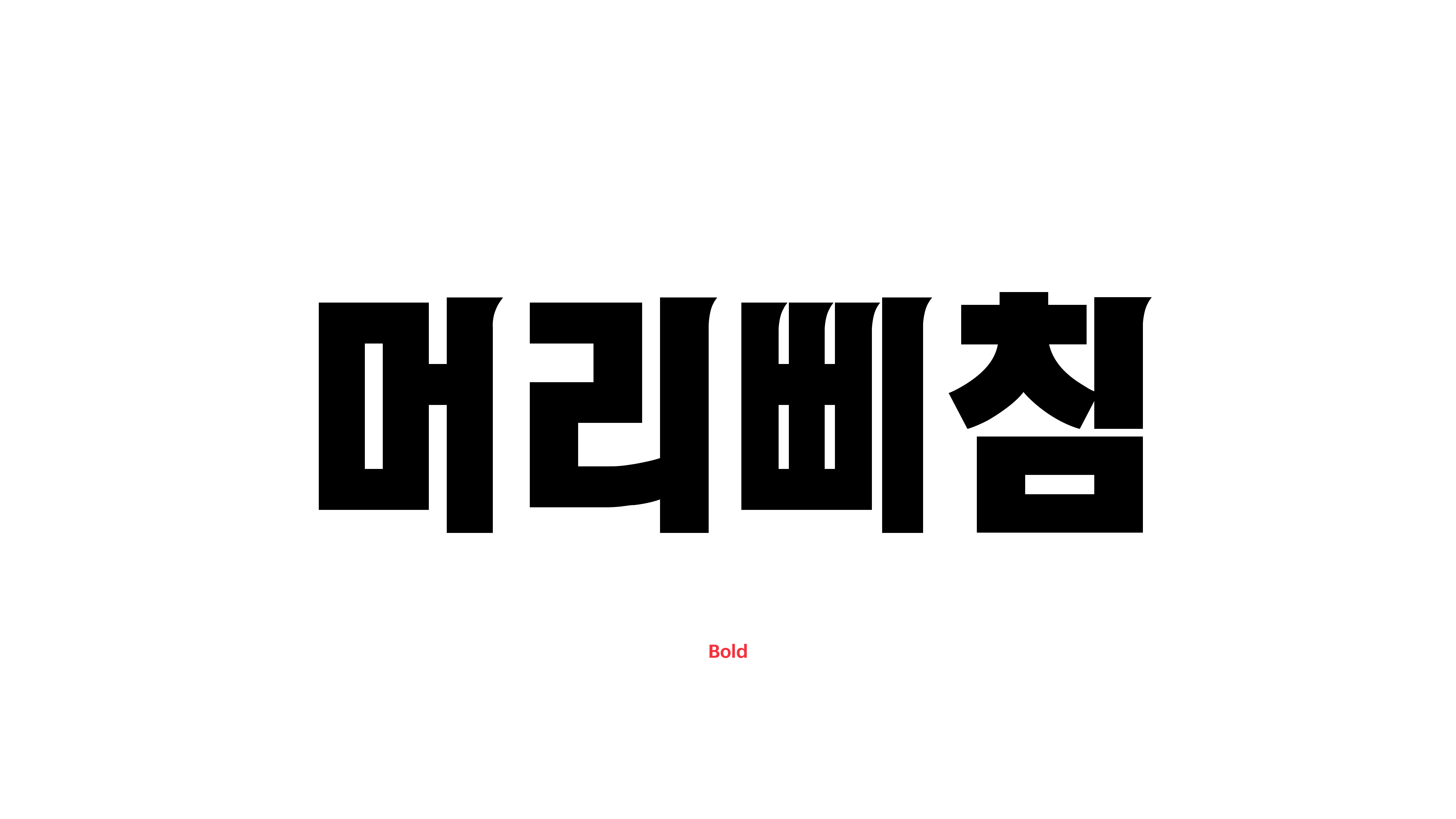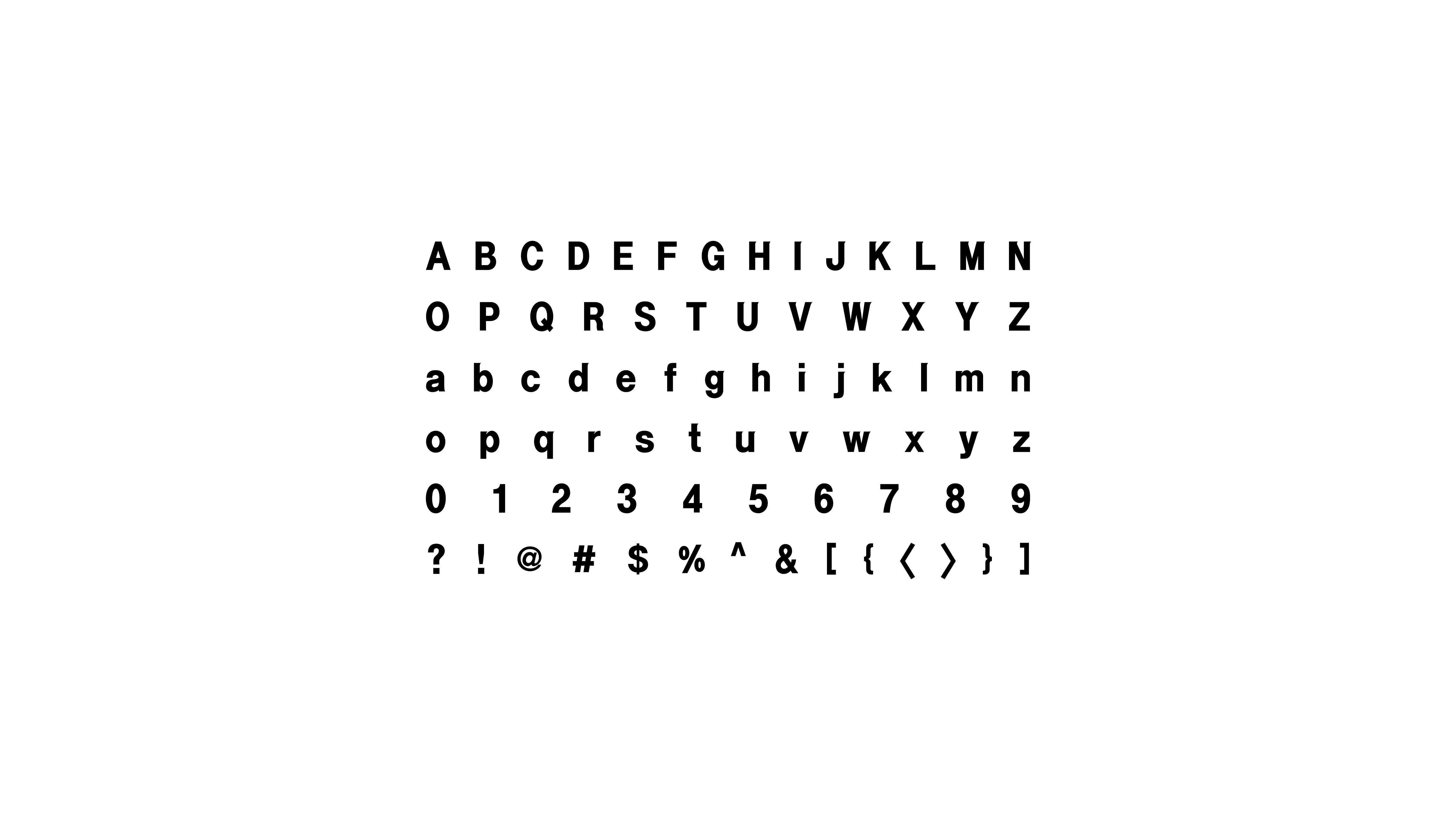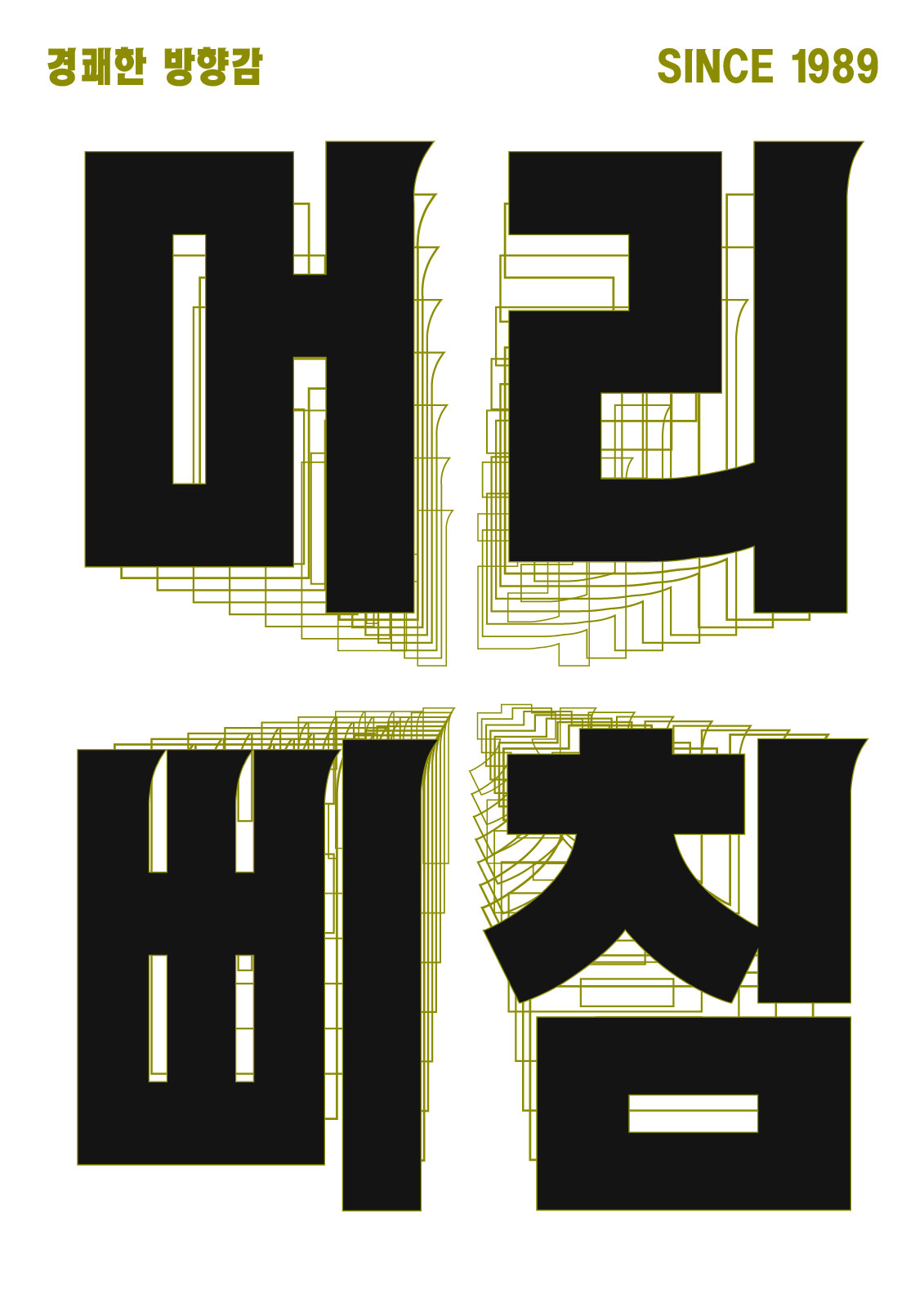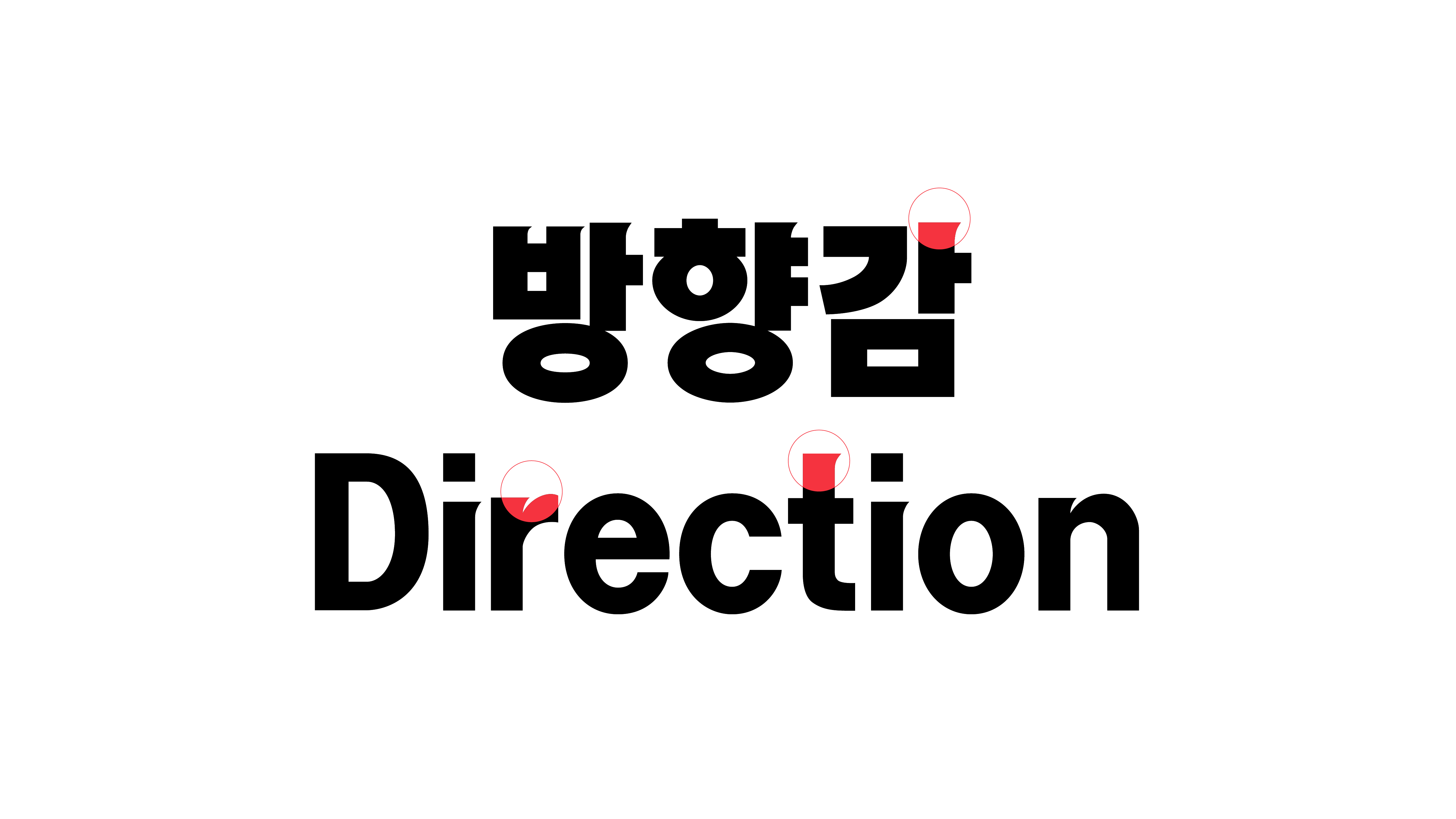
머리삐침
Yoon 머리삐침
늘 정확하고 딱딱한 줄만 알았던 내 상사의 똑단발 머리카락도 멋대로 삐치는 날이 있답니다. 머리정체에 삐침을 추가했을 뿐인데, 경쾌한 방향감과 색다른 긴장감이 유쾌하고 자유로운 기분을 선사하지요. 유독 딱딱해 보이는 제목에 웃음기를 더하고 싶은 날, 머리삐침체 어떠세요?